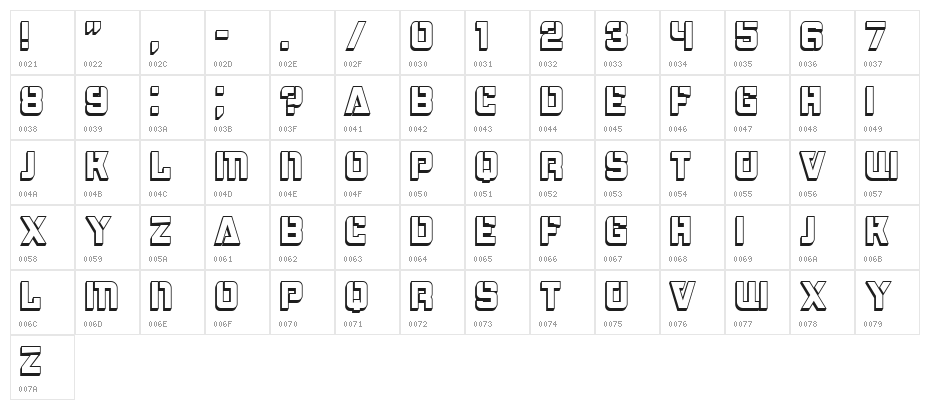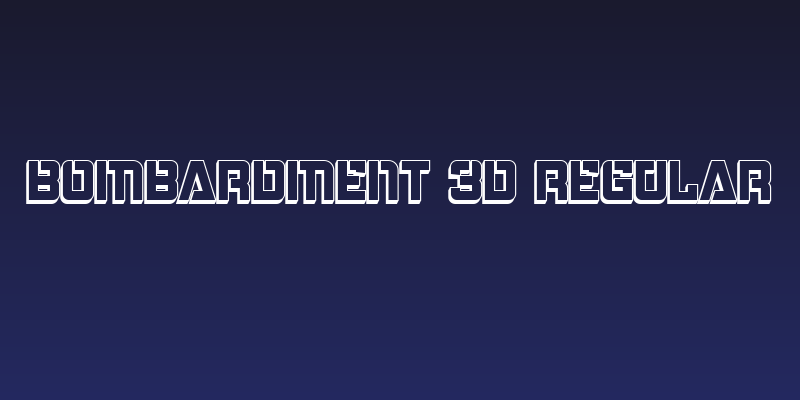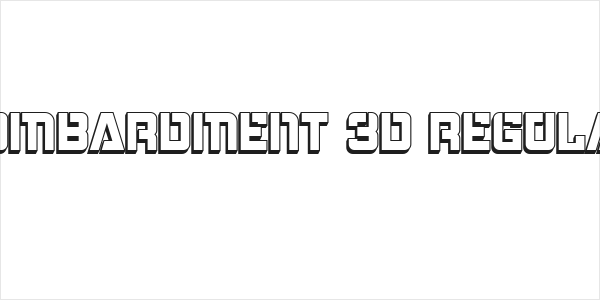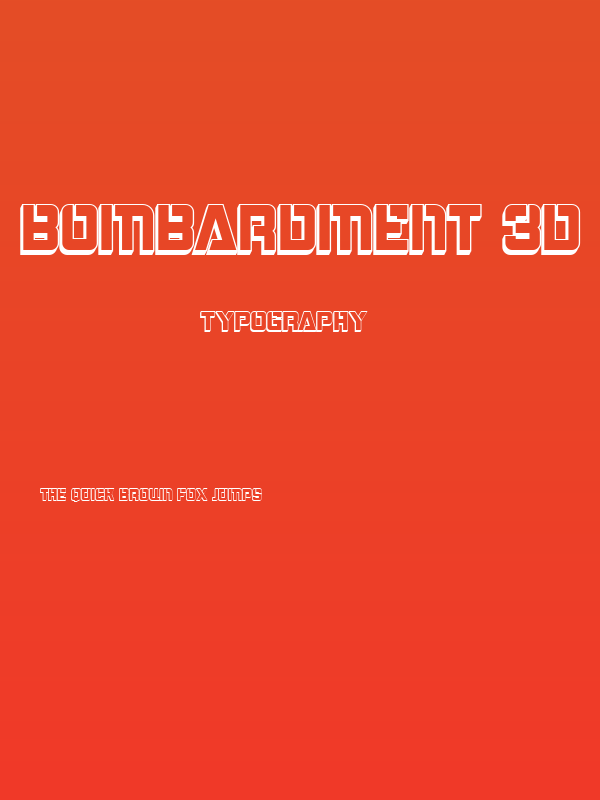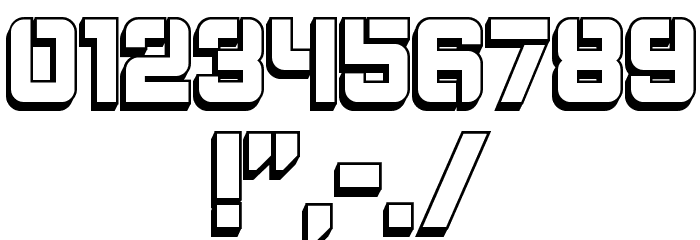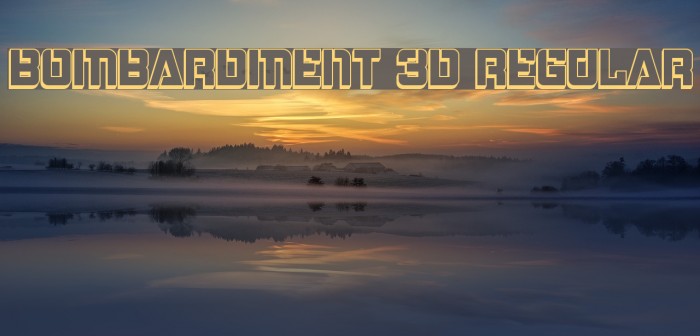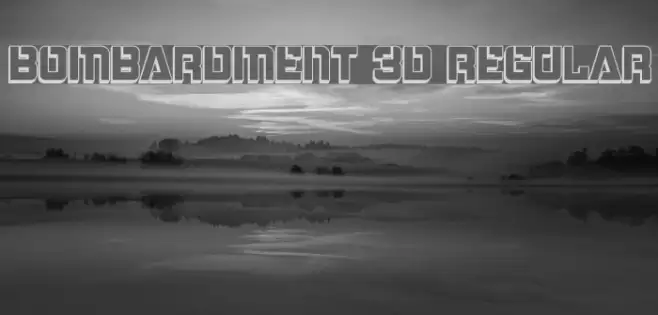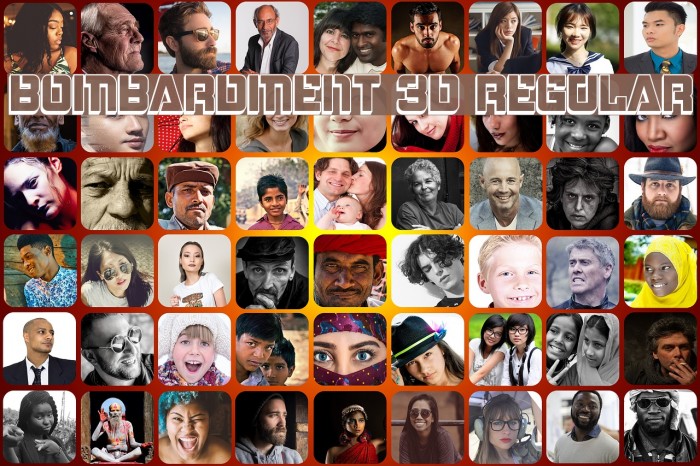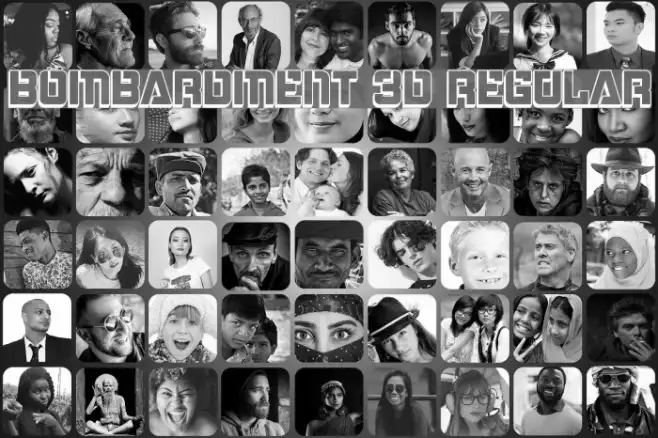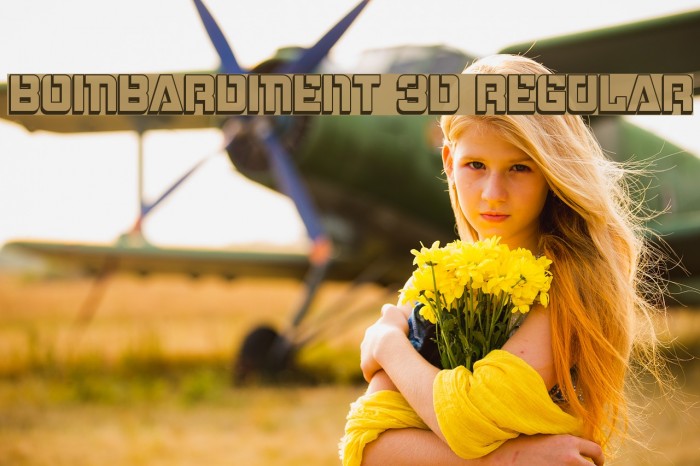
Bombardment 3D Regular Font
| Projets proposés | Ideal for video game titles, movie posters, branding for tech companies, and any design needing a modern, impactful look. |